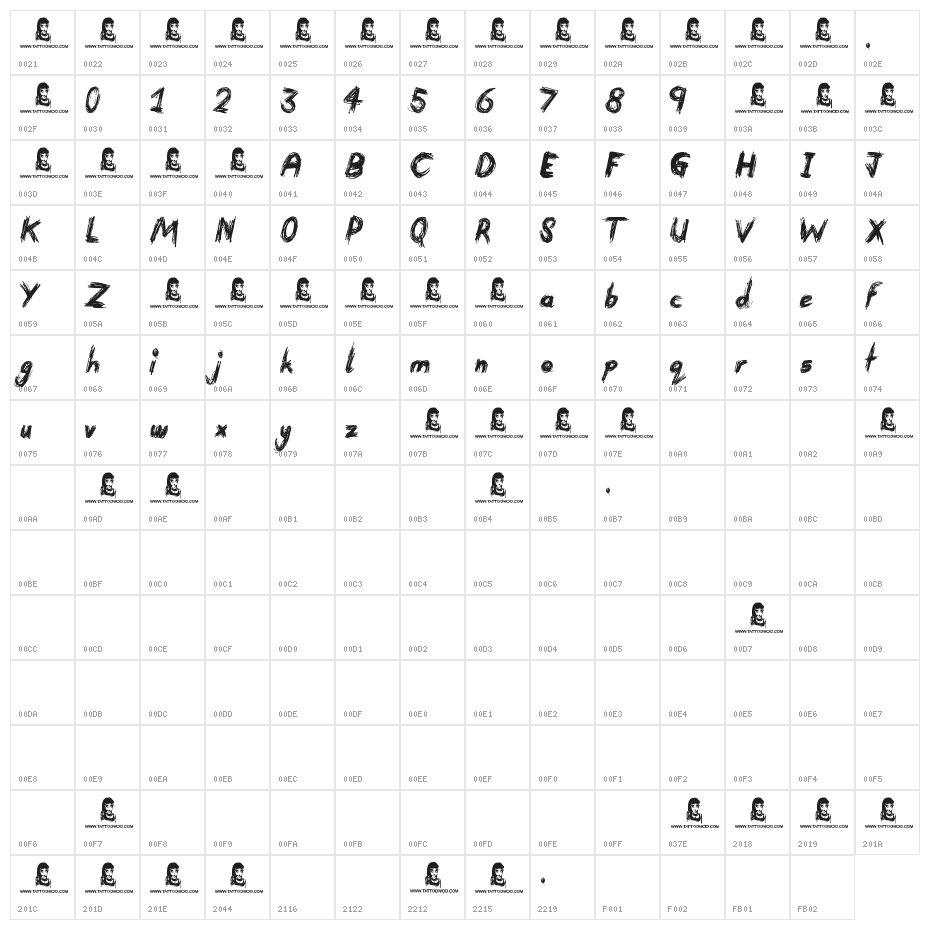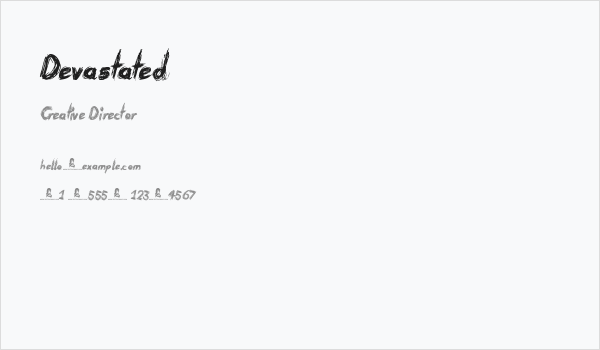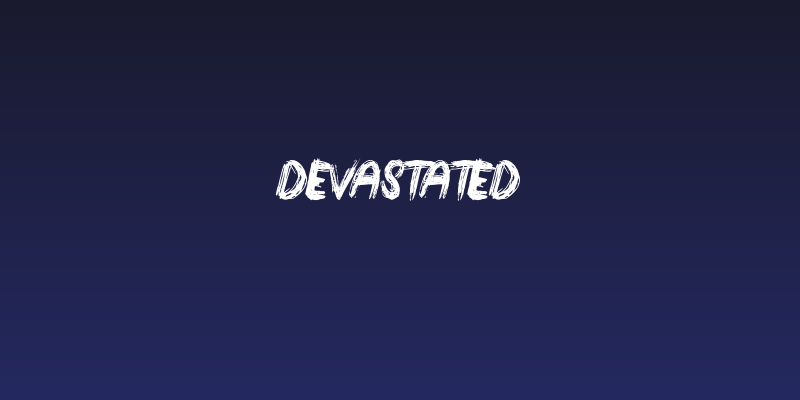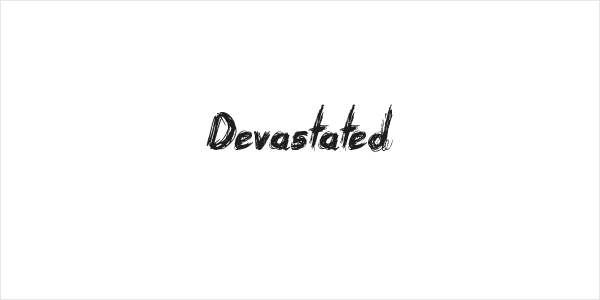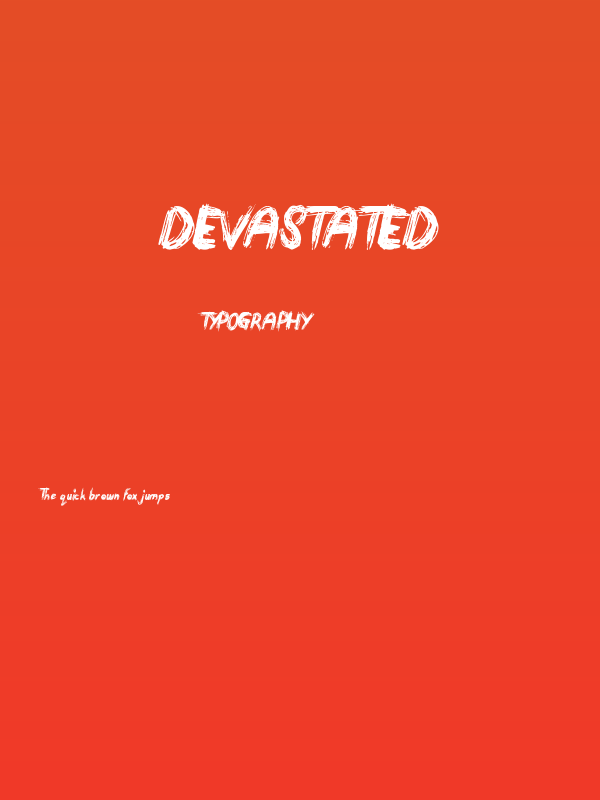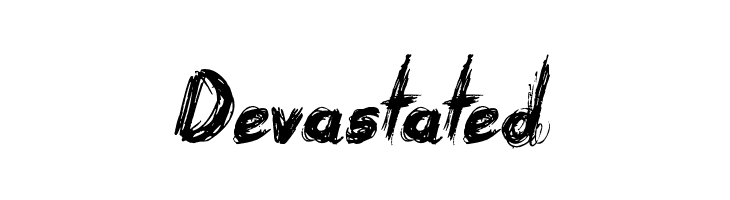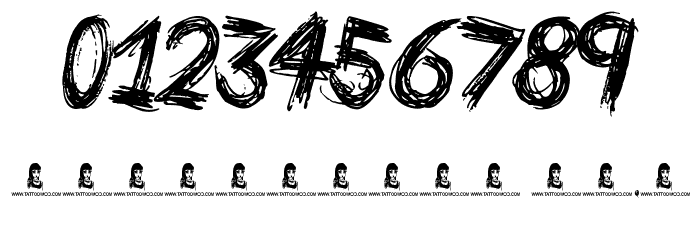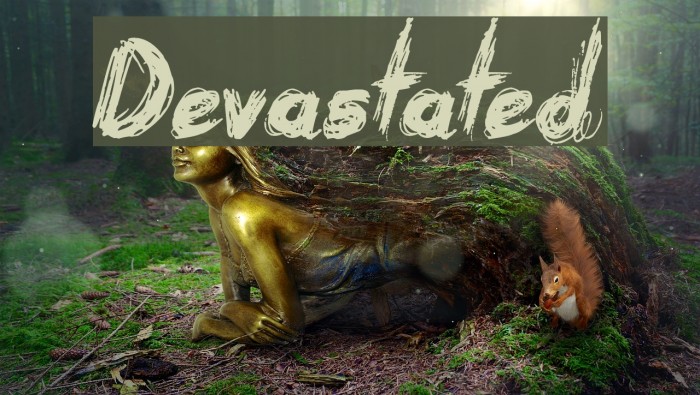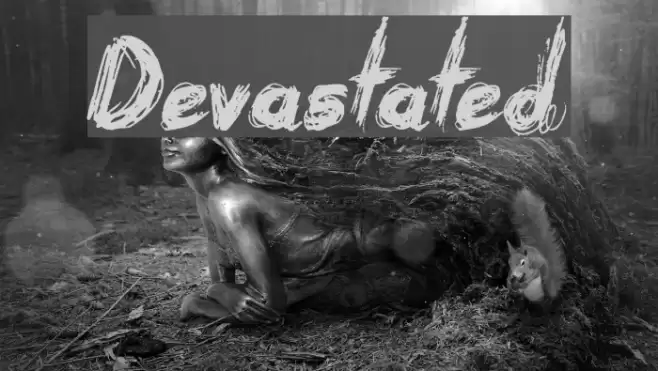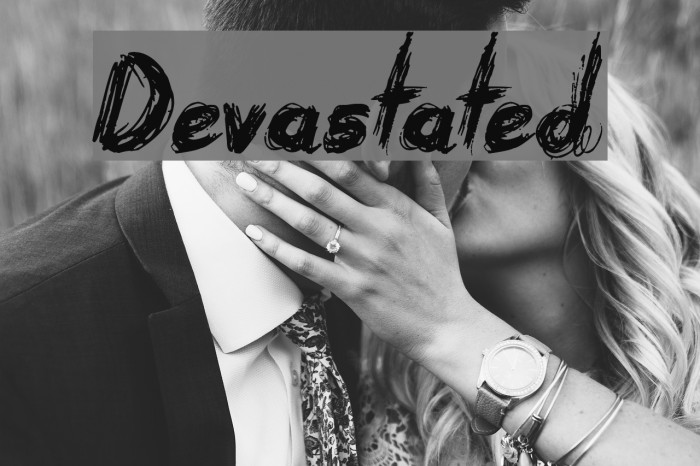
Devastated Font
| النمط العام | Grunge, Urban |
| حالة الاستخدام | Headlines, Posters, Artistic Designs |
| مشاريع مقترحة | Ideal for album covers, posters, street art designs, and any project needing a raw, edgy aesthetic. |